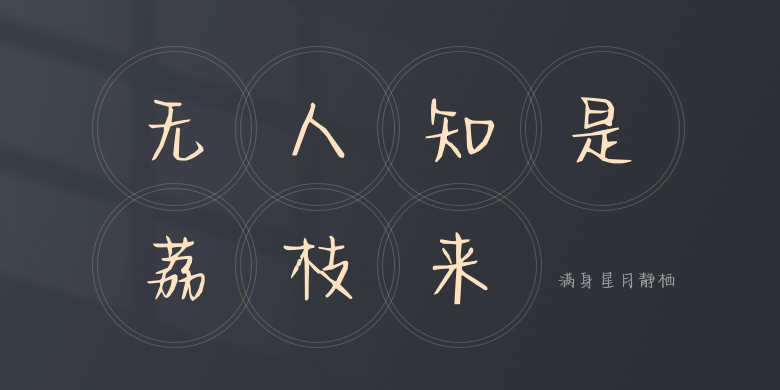
满身星月静栖
满身星月静栖,这款字体结构工整、笔画清晰,兼顾美观与易读性,适用于标题、正文、海报、包装、LOGO 等多种场景。字形优雅稳定,风格百搭耐看,适配日常排版与创意设计,让文字呈现更舒适、更具质感。满身星月静栖一笔一画,皆是细节,以均衡的比例、流畅的线条打造舒适视觉体验,字形端正大气,风格简约现代。无论是商业设计、品牌宣传还是日常排版,都能轻松驾驭,让文字更有格调与力量。满身星月静栖字体下载。